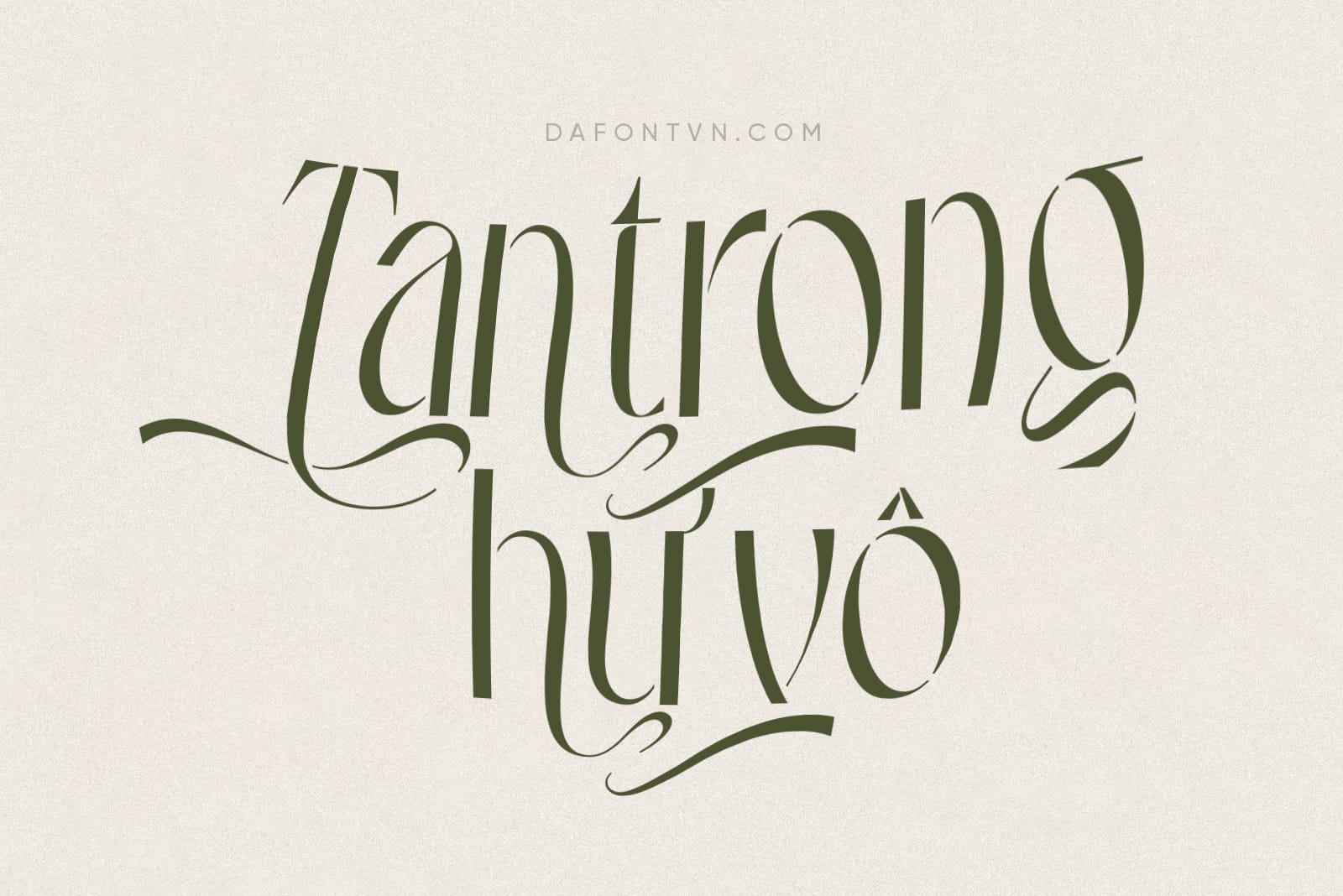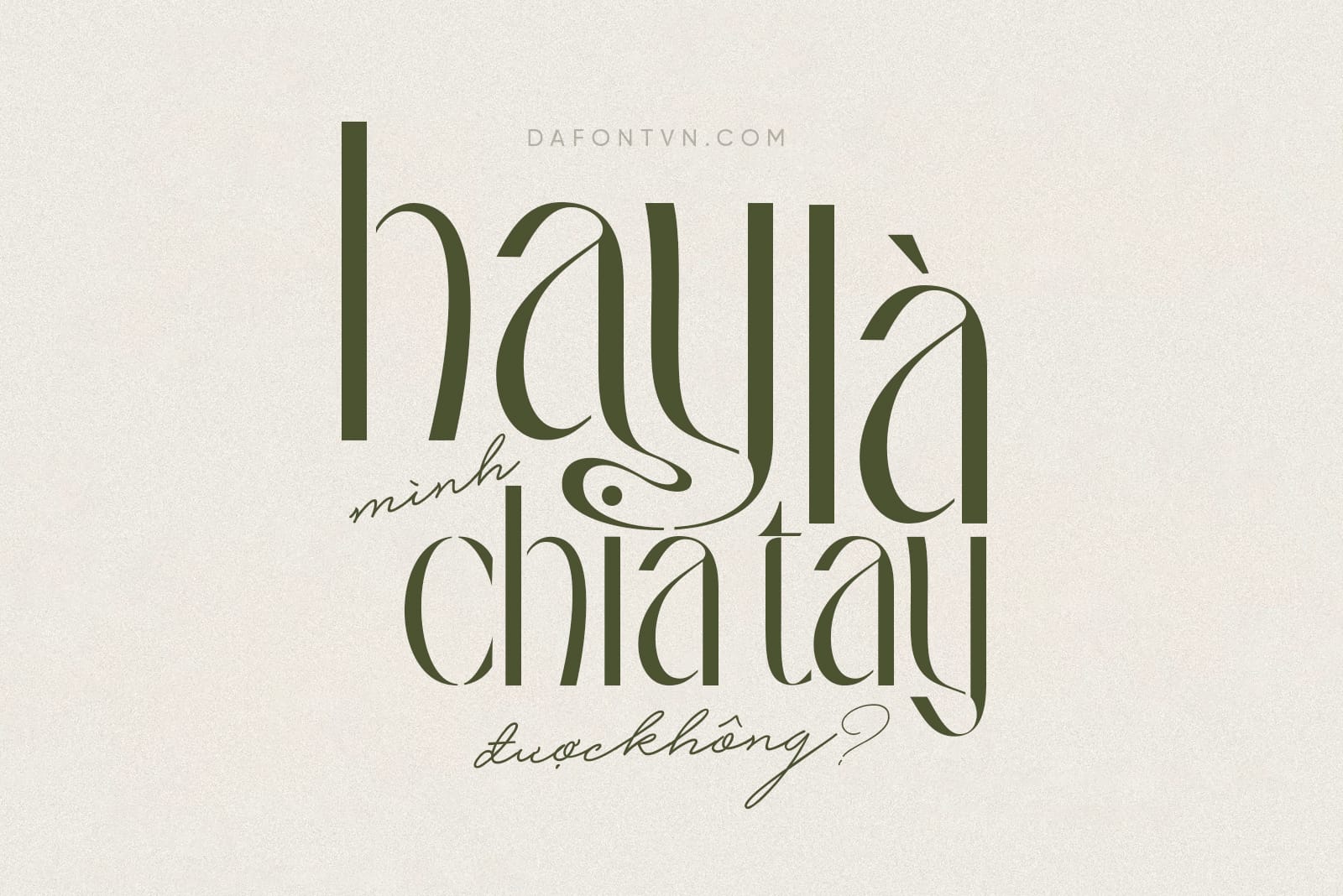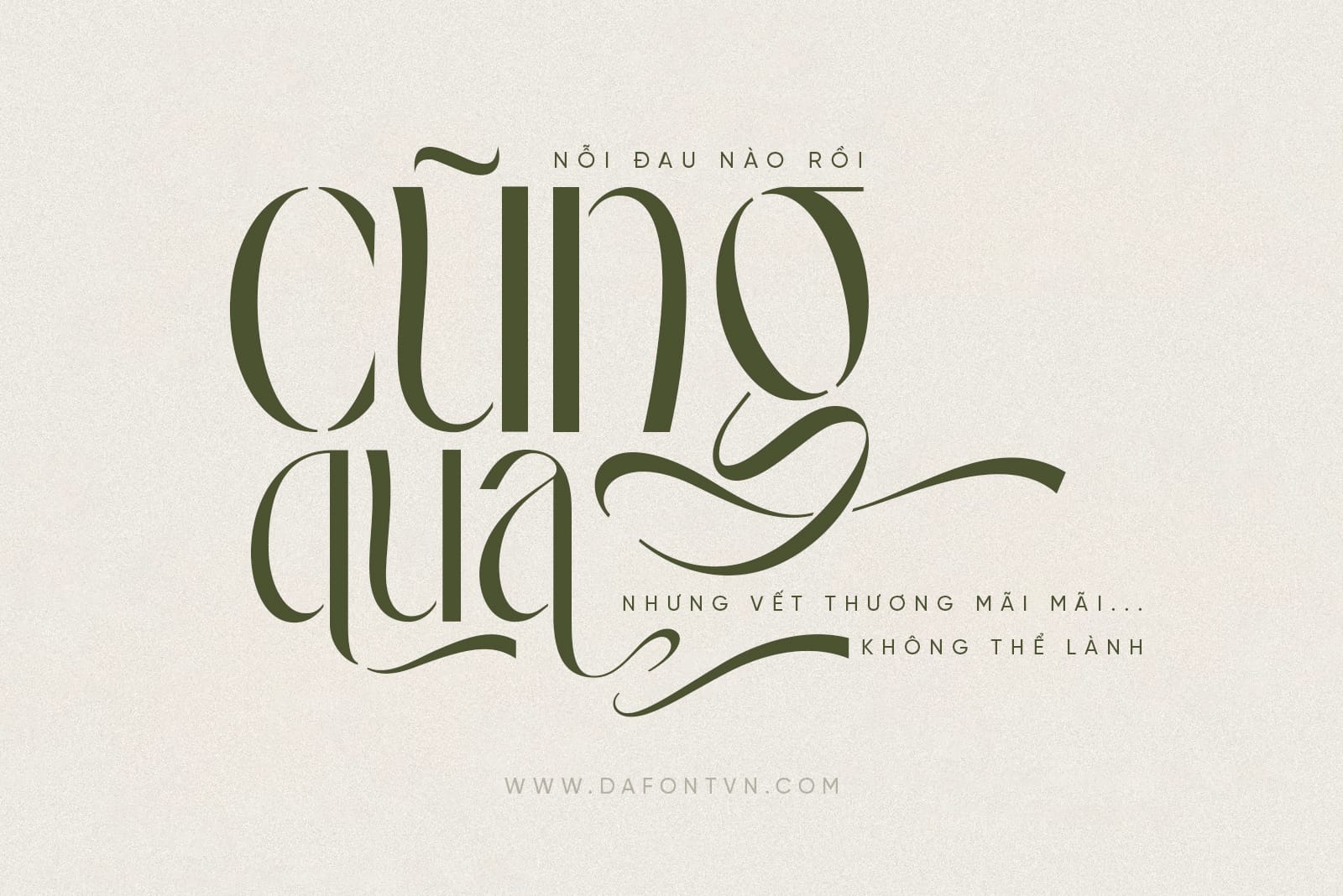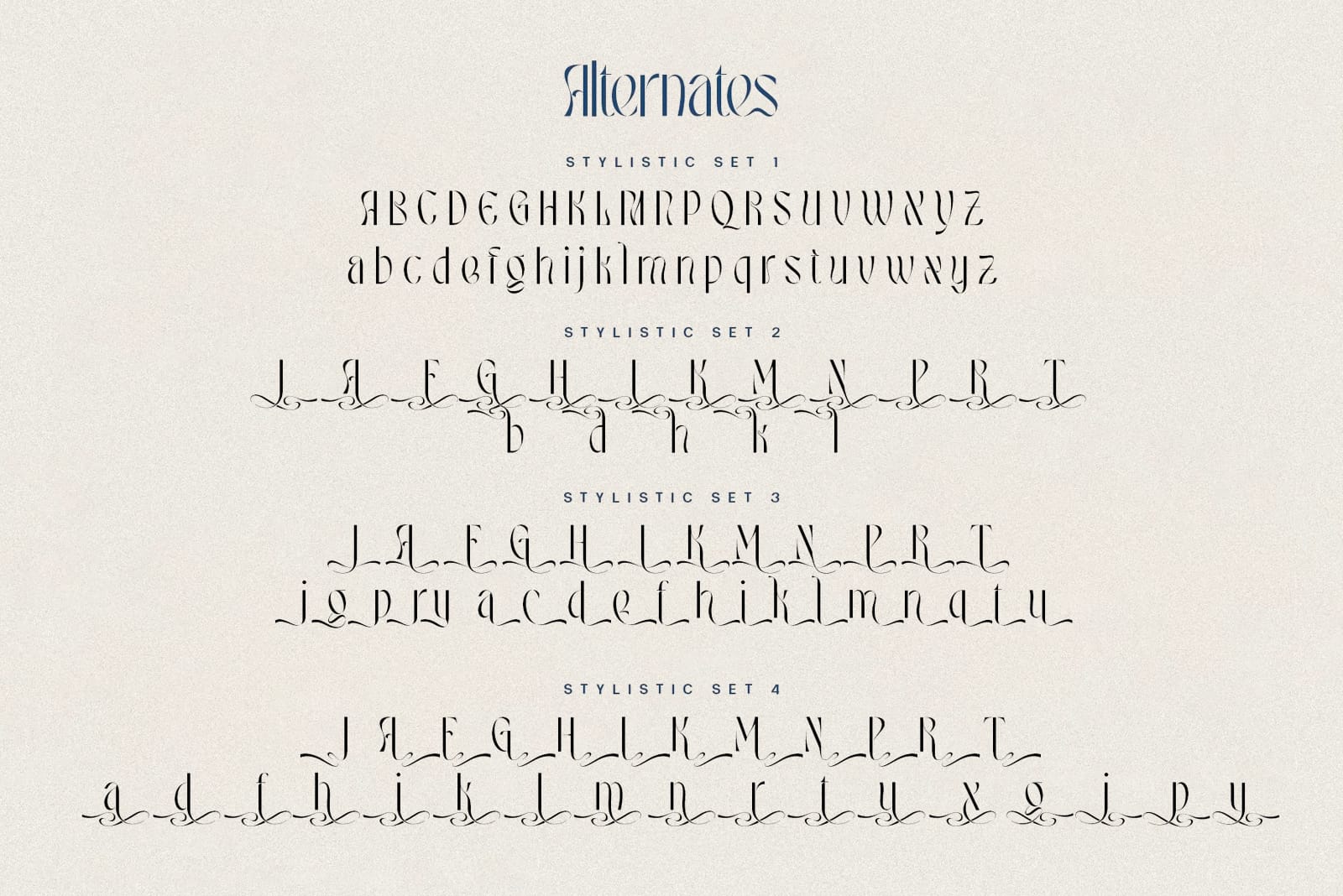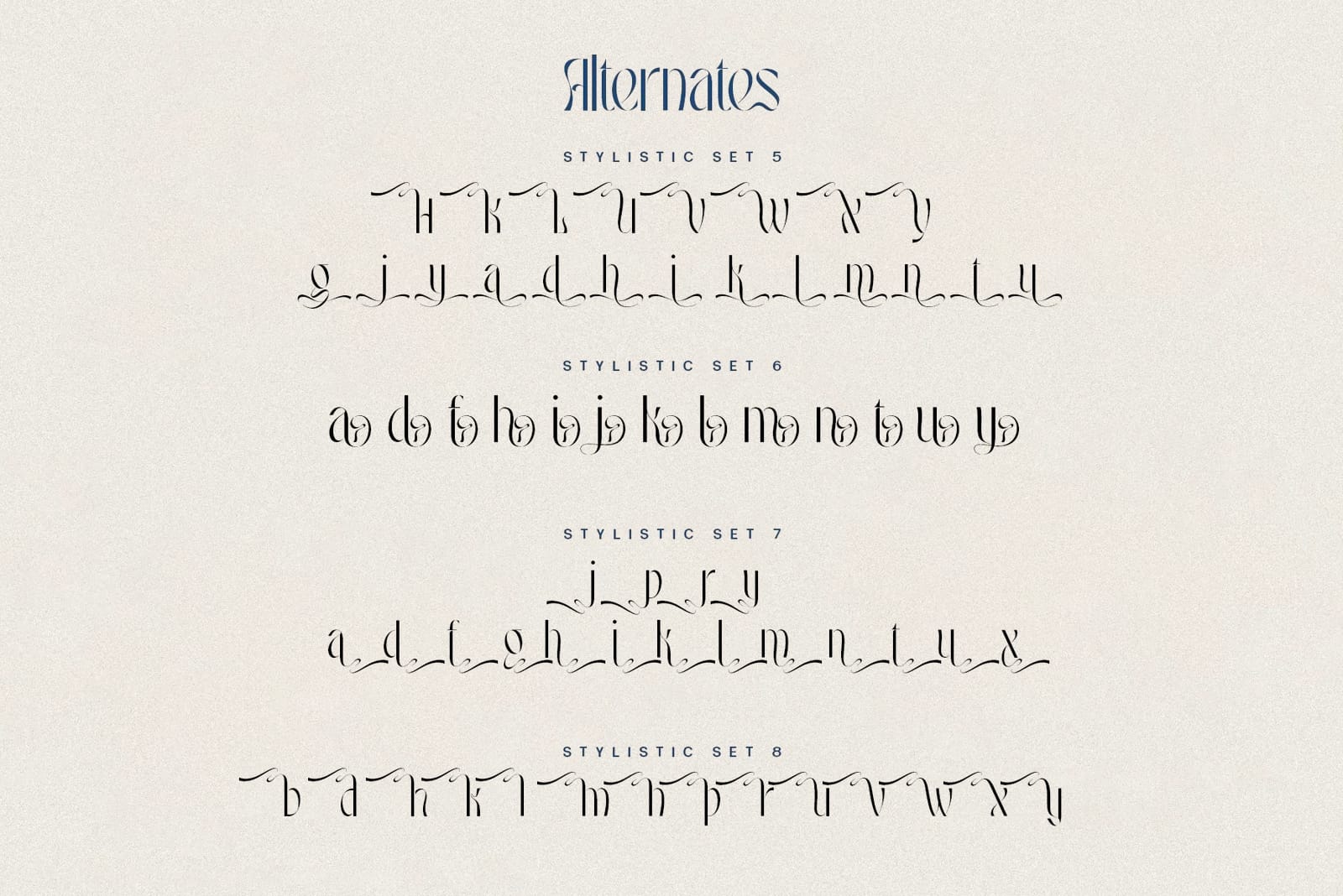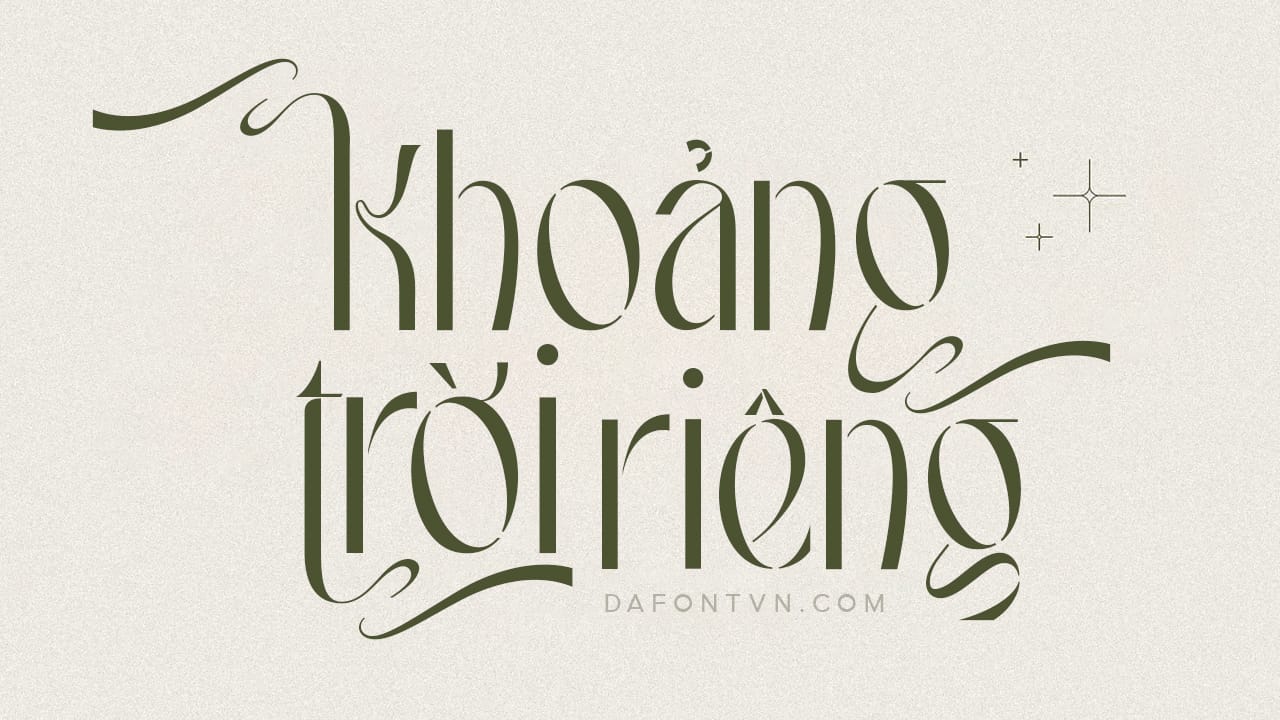
MANDAY TYPEFACE – 1 kiểu font chữ hiển thị hiện đại và tuyệt đẹp. Manday font là một kiểu font stencil được thiết kế mang hơi hướng cổ điển nhưng vẫn mang một vẻ đẹp thanh lịch và hấp dẫn cho bất kỳ thiết kế nào bởi các đường nét của font được vẽ tinh tế.
Ngoài sự thay đổi trong phông chữ MANDAY, cũng có nhiều hình dạng ký tự thay thế và các chữ ghép Discreati tĩnh độc đáo. Vì vậy đây có thể là 1 font chữ không thể thiếu trong bộ sưu tập font việt hóa của bạn.
Manday rất dễ sử dụng cho bất kỳ thiết kế nào, đặc biệt là những thiết kế cần đến 1 font chữ hiển thị hiện đại, nổi bật, ấn tượng và khác biệt, ngoài ra phông chữ này có thể sử dụng trong bất kỳ chương trình thiết kế và phi thiết kế nào bởi font được hỗ trợ bởi PUA.
Đặc biệt hơn, font Manday Typeface Việt hóa chứa 800 glyph với nhiều tùy chọn thay thế độc đáo và cực đẹp.